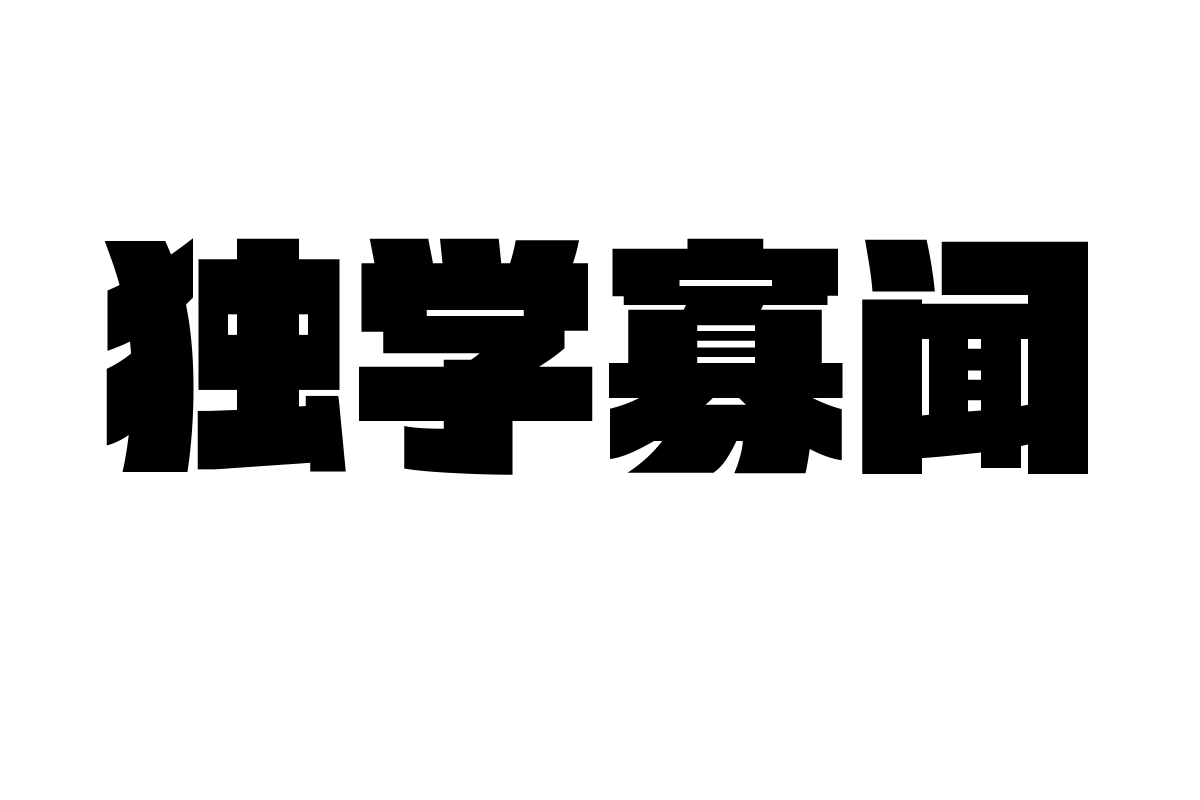
锐字潮牌时尚魔黑字体是一款具有现代感和潮流元素的字体。它的设计风格独特,线条流畅,给人一种时尚、前卫的感觉。这款字体适用于各种商业广告、品牌宣传、设计项目等场合,能够有效地提升品牌形象和吸引力。
锐字潮牌时尚魔黑字体的特点如下:
1. 简洁明了:字体结构紧凑,笔画清晰,易于阅读和识别。
2. 时尚前卫:采用现代的设计元素,如斜线、曲线等,使字体更具时尚感。
3. 易读性强:字体大小适中,间距合理,使得文本内容易于阅读和理解。
4. 适应性强:适用于各种印刷媒介,如纸张、布料、金属等,具有较高的实用价值。
5. 创意十足:字体设计独特,具有一定的艺术性和观赏性,能够吸引消费者的注意力。
总之,锐字潮牌时尚魔黑字体是一款适合现代商业环境的字体,能够帮助企业塑造独特的品牌形象,提升市场竞争力。